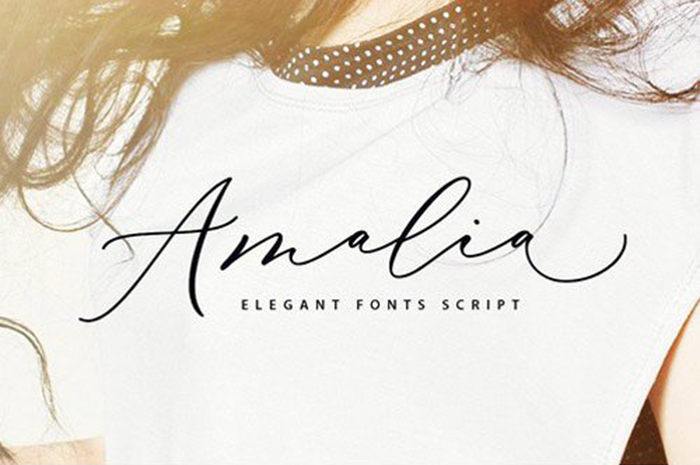
Amalia Script Font – Fonte Grátis
Amalia Script Font
A Amalia Script Font é uma delicada fonte com traços contemporâneos e sofisticados, perfeita para estilos fashionistas e modernos. Suas linhas elegantes e arredondadas destacam-se nas marcas de moda, sites de e-commerce e blogs que abordam tendências. Ela se adapta como títulos de livros, design de convites, slogans e até mesmo gráficos para embalagens ou panfletos promocionais. Com um charme próprio, a Amalia atende aos requisitos das marcas que desejam transmitir elegância e refinamento através da tipografia. A fonte é uma escolha perfeita para qualquer marca que deseja destacar-se em seu campo de atuação, seja ela títulos de livros, cartões de convite ou até mesmo sobre-títulos de sites de moda.